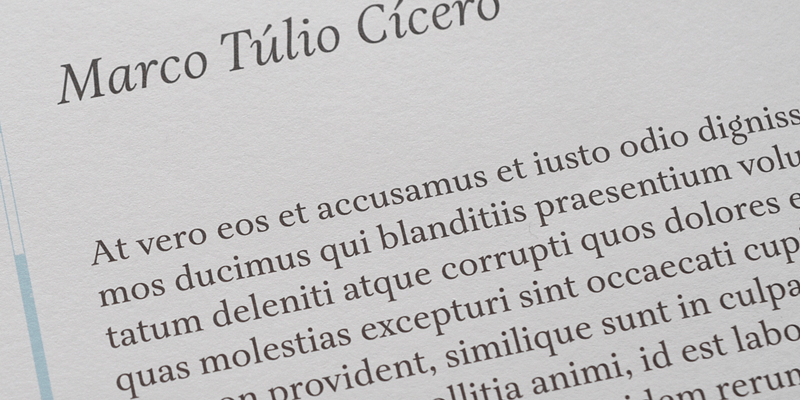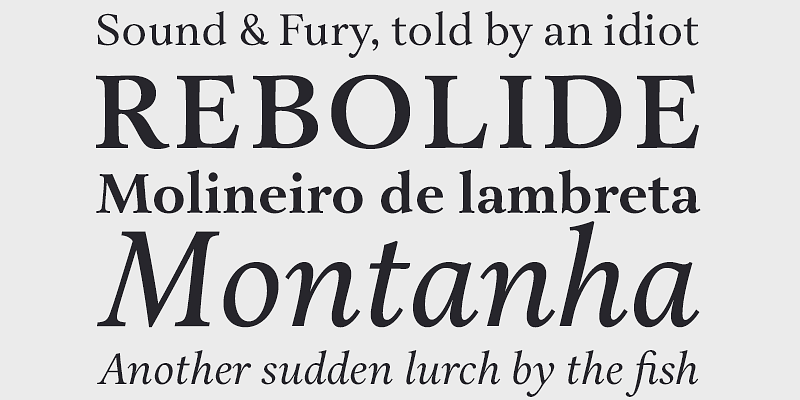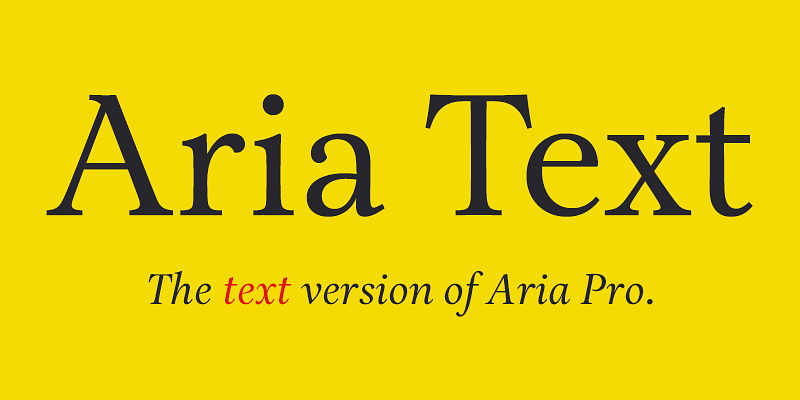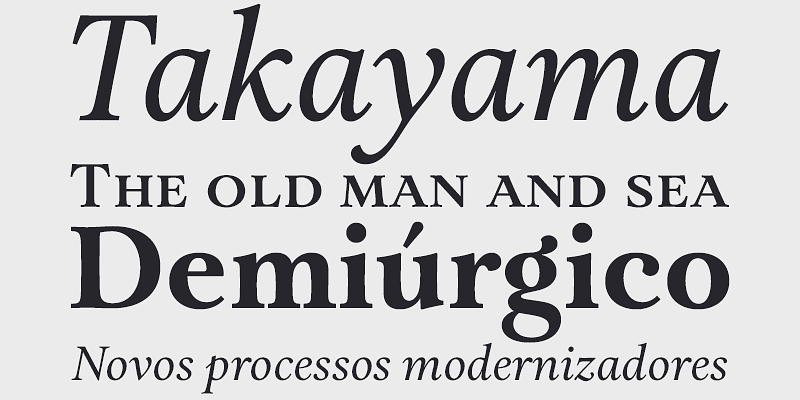
Aria Text ist eine freie Interpretation des historischen Transitional-Stils, jedoch mit einem gemäßigteren Kontrast zwischen dicken und dünnen Strichen und einem weniger formalen Aussehen.
Rui Abreu ist ein portugiesischer Schrift- und Grafikdesigner. Er hat Grafikdesign an der FBAUP (Faculdade de Belas Artes da Universidade do Porto) studiert und 2003 dort seinen Abschluss gemacht.
Parallel zu seiner Tätigkeit als Mediendesigner arbeitet Rui Abreu seit 2006 an kommerziellen Schriften.